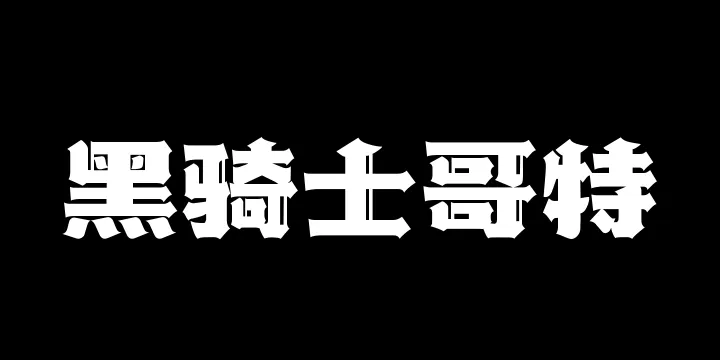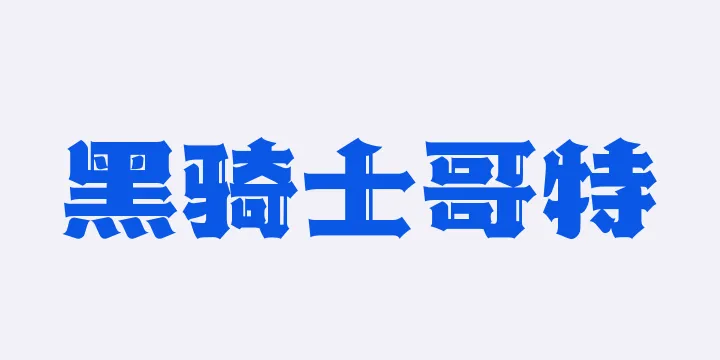
山海黑骑士哥特W By 山海字库 商用字体
字体简介: 山海黑骑士哥特,是一款全新的字体,包含简繁汉字9169个,符号200+个,是一款哥特风汉字字体。该字体融合了西方哥特元素,字体独特,新颖华丽。汉字艺术与西方文字的融合,如夜空中闪烁着暗黑光芒;个性鲜明的字体特征,散发着神秘而高冷的气息。在华丽而不失婉约中,感受哥特风的魅力。